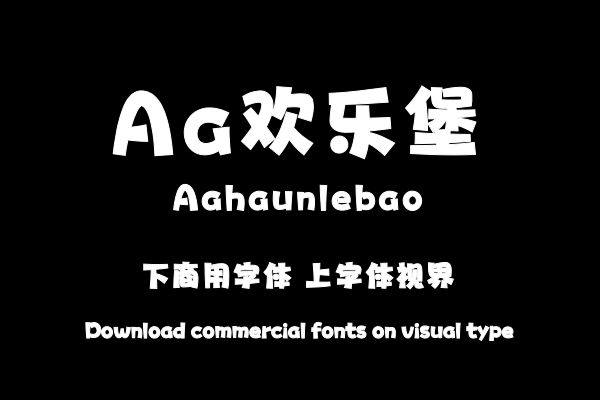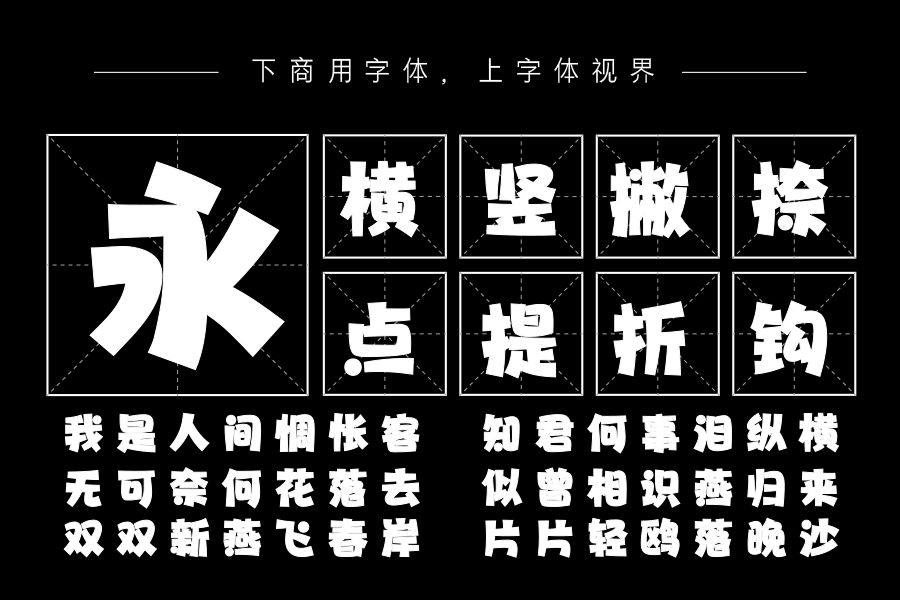
字形粗胖可爱,整体形态敦厚,轻微的弧度和笔画两端的粗细变化使字体变得更分灵活,将部分笔画用圆点替代,为字体增添了许多灵气。购买须知:“下载服务费”与“字体VIP”所获得字体 仅用于个人非商用, 商用请联系付费授权。本字体为电脑用字,手机没有root权限不支持直接手机换字(手机如何root,请自行百度搜索教程)。购买前请先 了解清楚后再付款 ,字体为虚拟产品无法回收 一旦购买不支持退款。